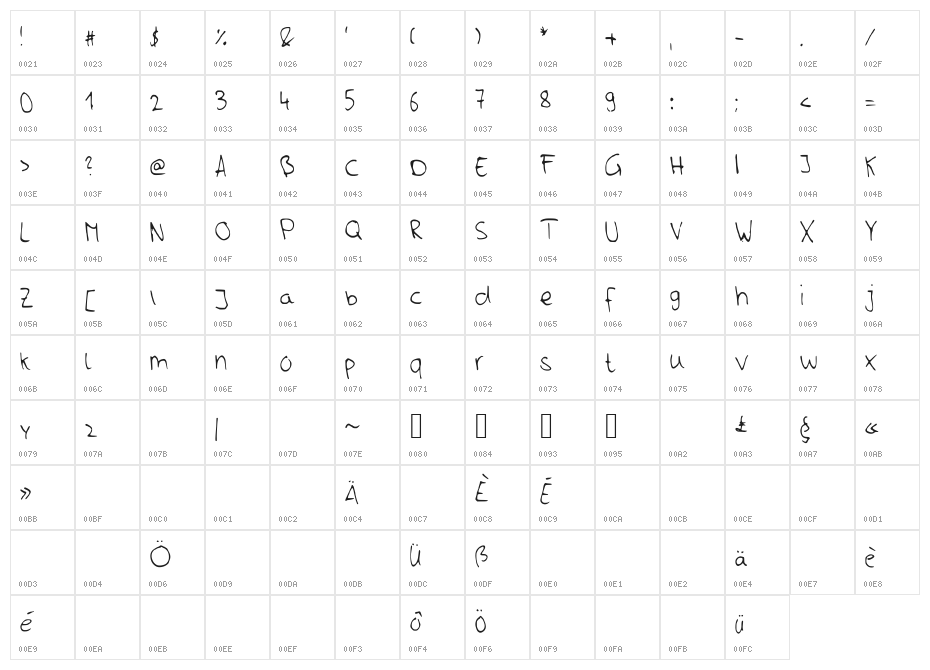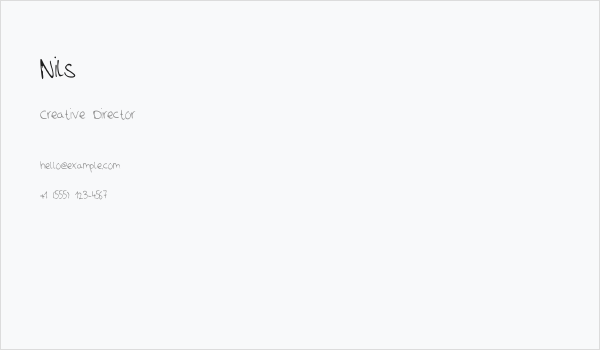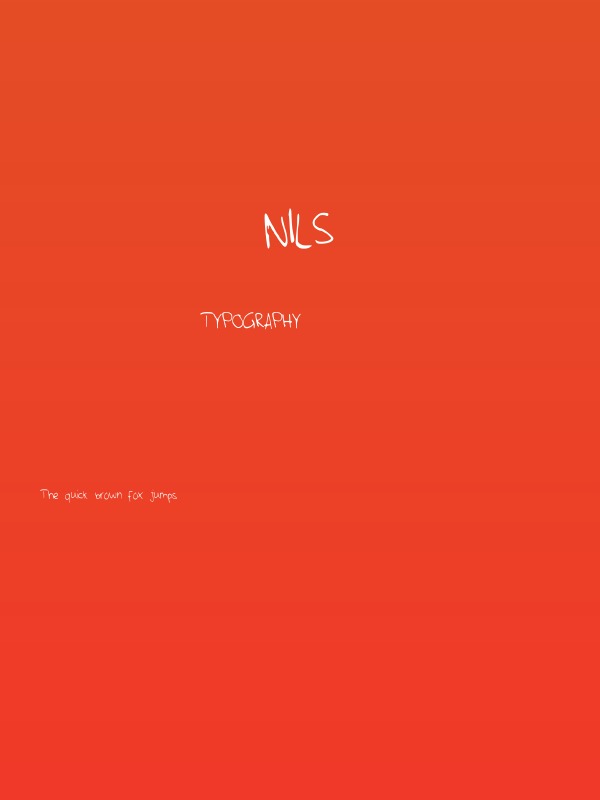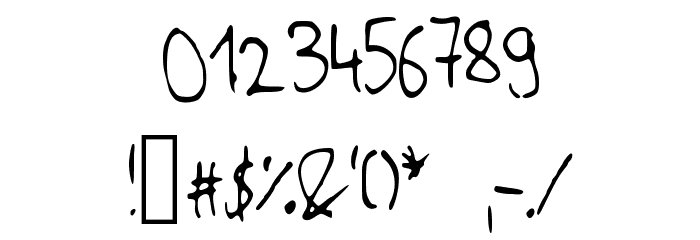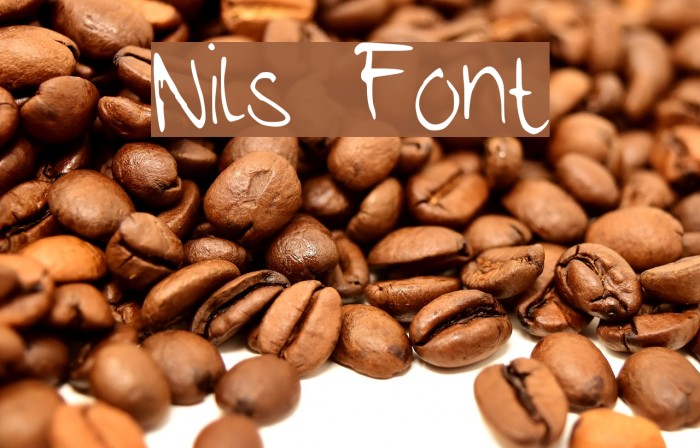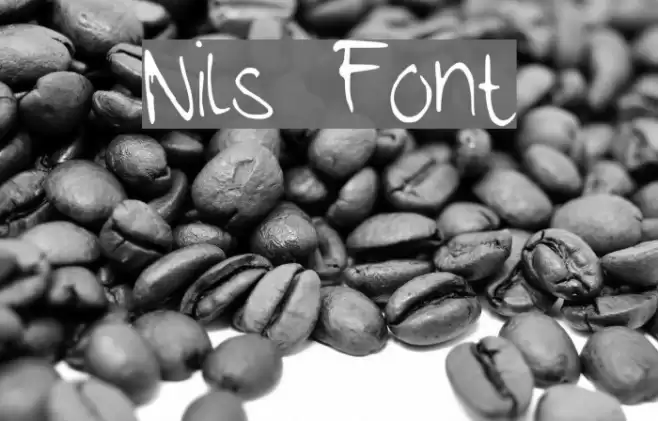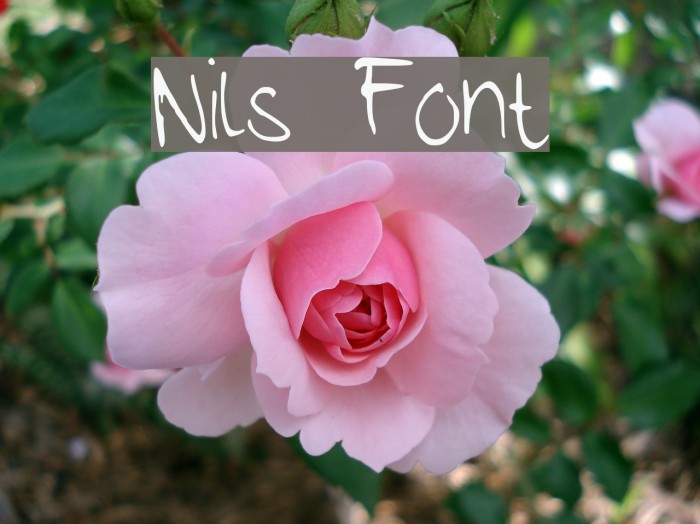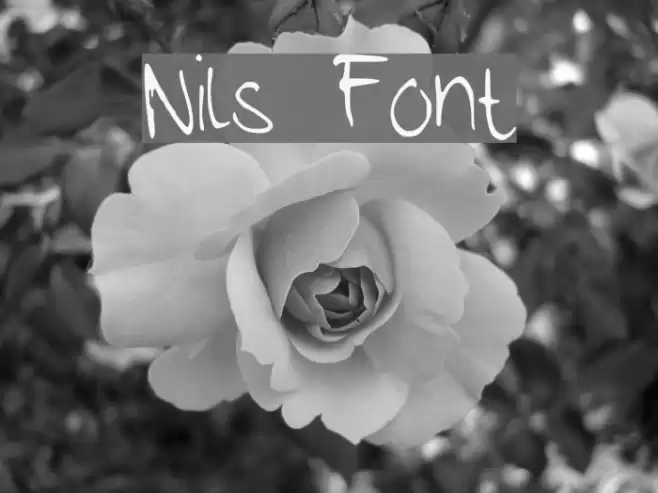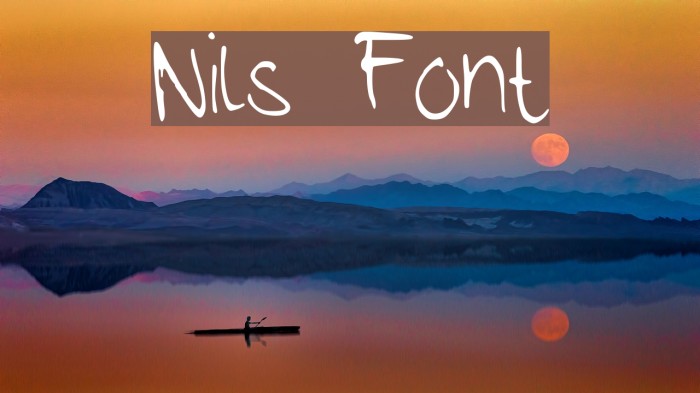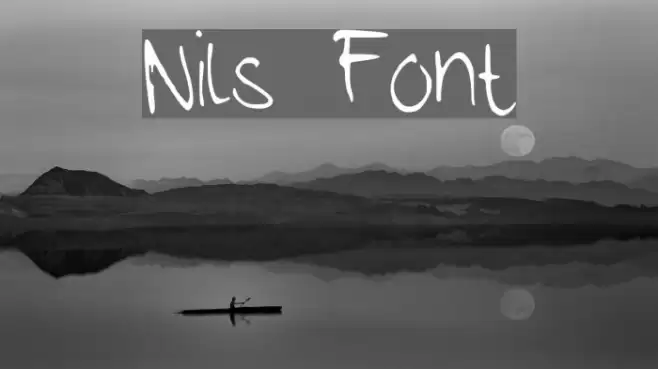
Nils Font
| النمط العام | Casual, Playful |
| حالة الاستخدام | Headlines, Informal text, Creative projects |
| مشاريع مقترحة | Ideal for greeting cards, personal invitations, children's books, and creative branding projects. |